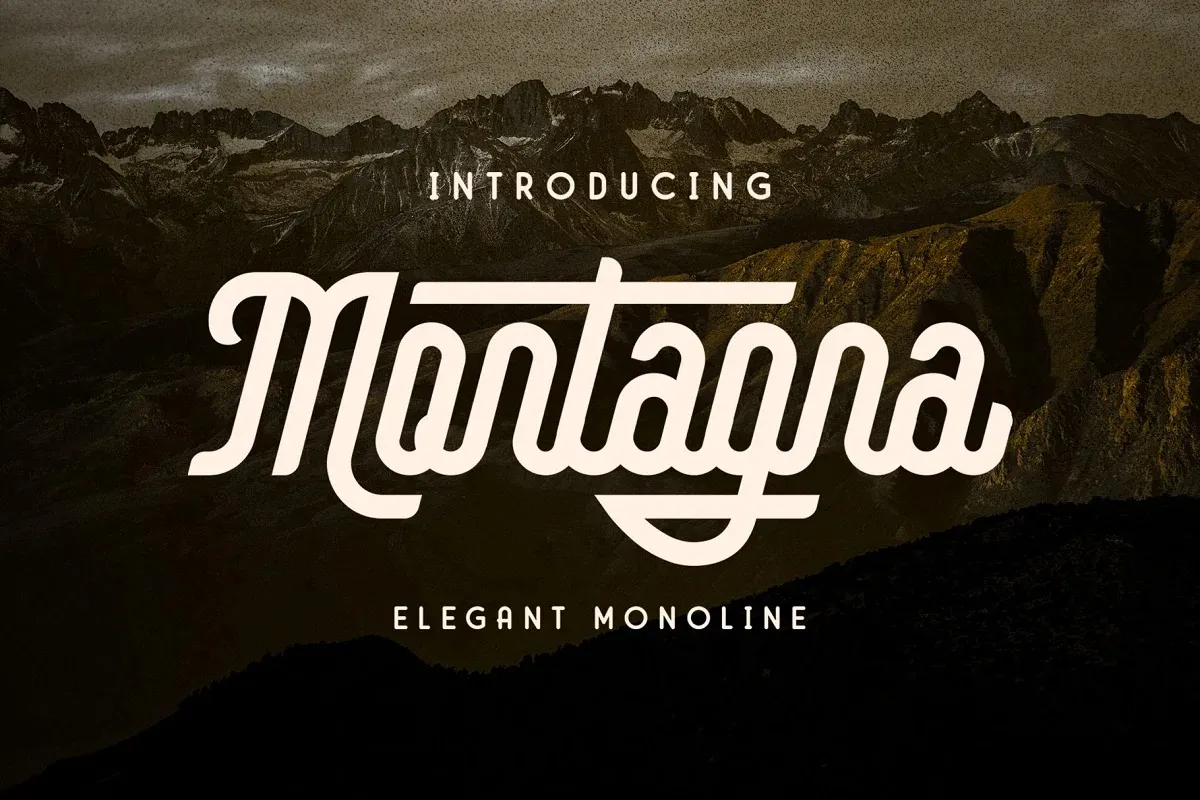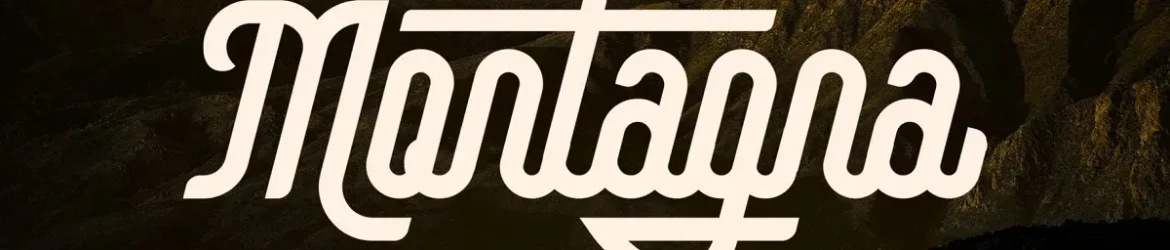
A Montagna Script Font é uma elegante tipografia monoline que captura elementos vintage, inspirada num retrô poster dos anos 80, neon-school e design moderno-vintage. Com sua linhas simples e antigos, a fonte transmite um ar nostálgico do passado, combinando o clássico com o contemporâneo de uma forma encantadora. Perfeita para criações que desejam manter uma conexão histórica sem perder a modernidade, esta fonte é perfeitamente adequada para criadores que buscam um estilo único e autêntico em seu trabalho. Com certeza, será sua escolha ideal para destacar mensagens de forma elegante em sites e documentos digitais.